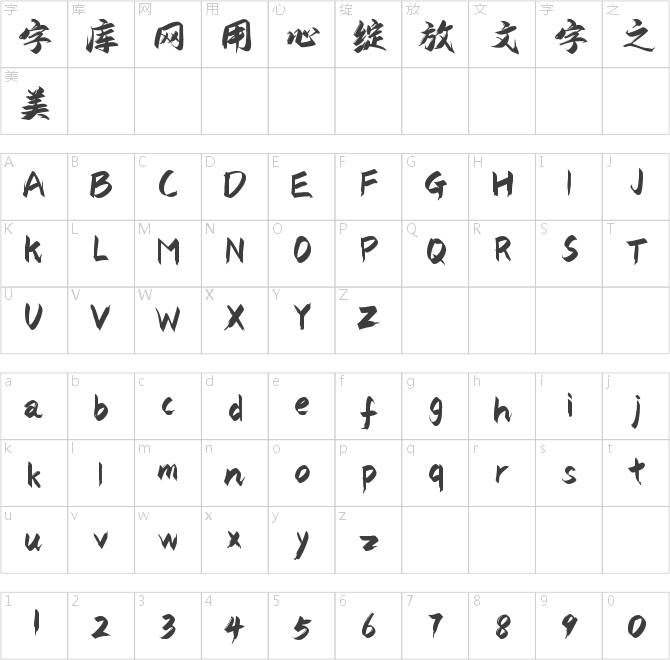
字魂210號(hào)-國(guó)風(fēng)少年體是一款書(shū)法字體。字體筆畫(huà)渾厚剛勁,筆法隨意靈動(dòng),字體的風(fēng)格熱情奔放,適用于宣傳設(shè)計(jì),商業(yè)類的品牌廣告和產(chǎn)品包裝設(shè)計(jì)。
字魂210號(hào)-國(guó)風(fēng)少年體字體zihun210hao-guofengshaonianti字庫(kù)是一款讓人賞心悅目、百看不厭的中文字體,適合各類廣告和產(chǎn)品包裝設(shè)計(jì)應(yīng)用,字體大小22.84MB,格式為ttf字體,上傳用戶是曾紹文,作者/版權(quán)方為字魂